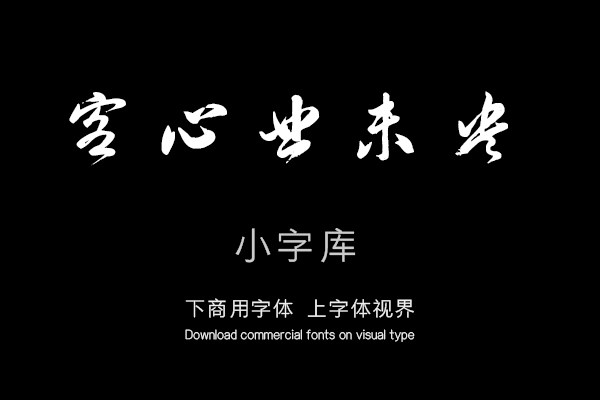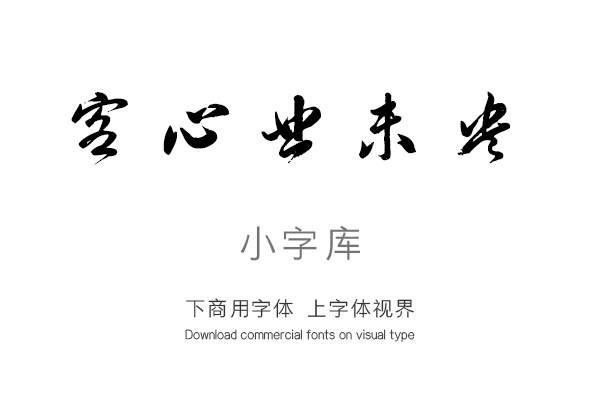
《汉标岳飞行草书谢眺诗》是一款根据宋朝岳飞《书谢眺诗》,经过再次调整制作的小字库,该小字库共收录了该真迹作品中约131个字体。单字授权
大江流日夜,客心悲未央。徒念关山近,终知返路长。秋河曙耿耿,寒渚夜苍苍。引领见京室,宫雉正相望。金波丽鳷鹊,玉绳低建章。驱车鼎门外,思见昭邱阳。驰晖不可接,何况隔两乡。风云有鸟道,江汉限无梁。常恐鹰隼击,时菊委严霜。寄言罻罗者,寥廓已高翔。 绍兴八年春三月既望岳飞